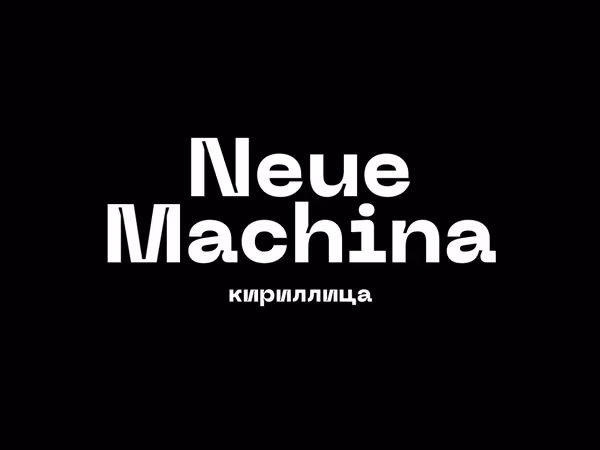
Neue Machina шрифт
Neue Machina - мощный кирилический и тщательно продуманный шрифт. Может похвастаться моноширинным и геометрическим шрифтом, а также явными и глубокими ловушками для чернил при более тяжелом весе.